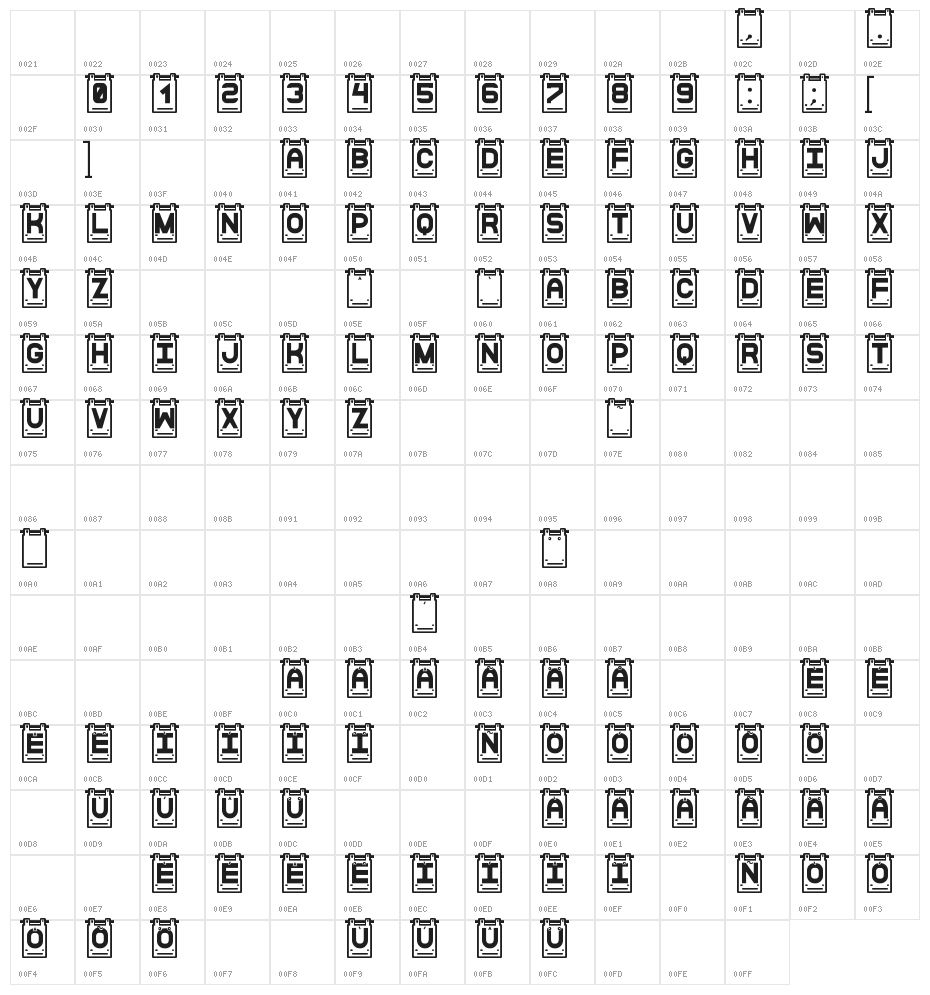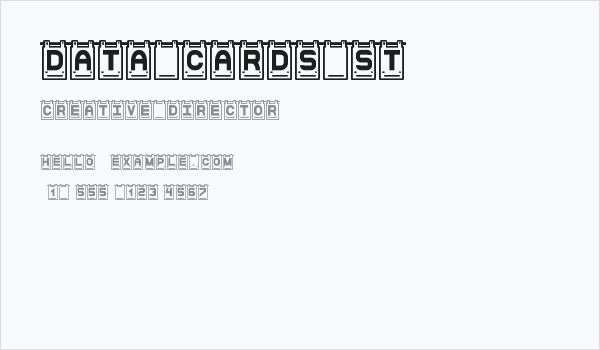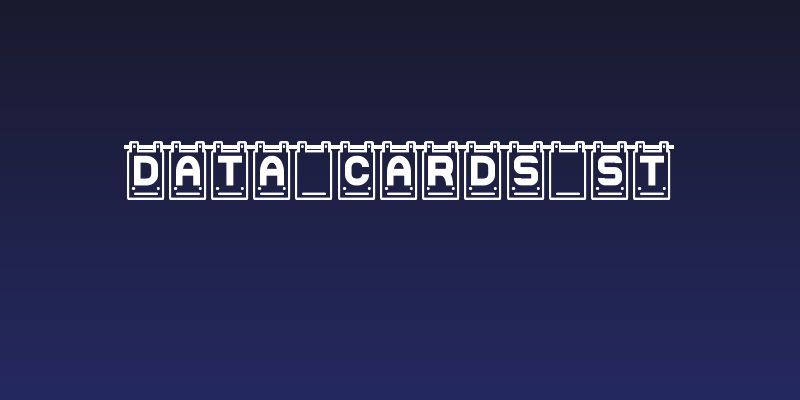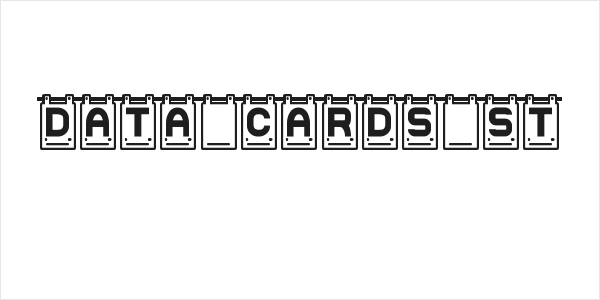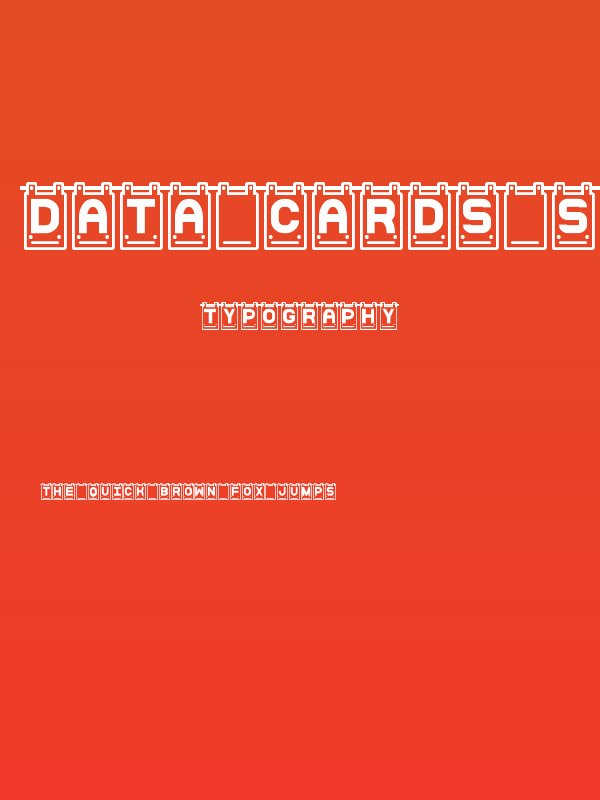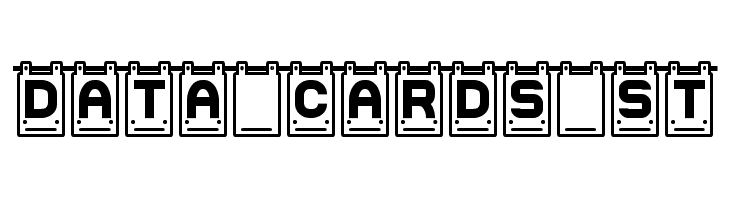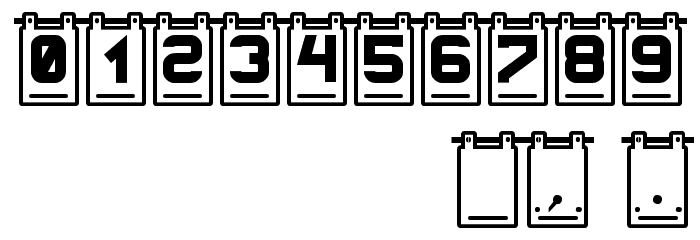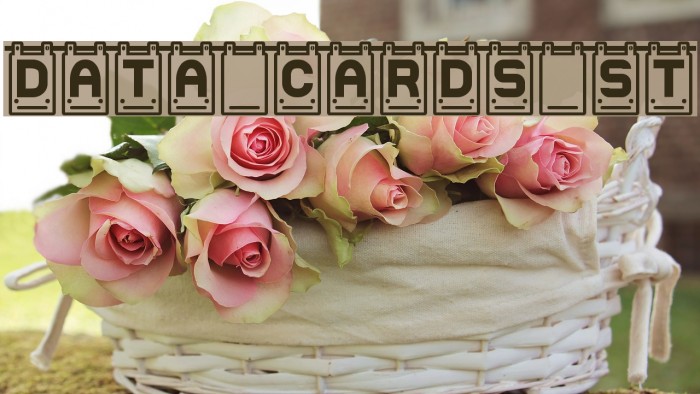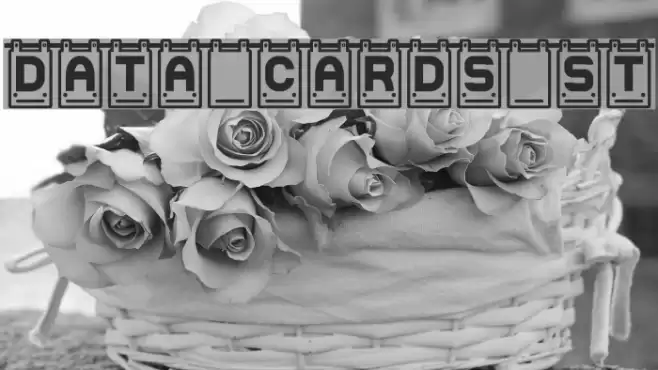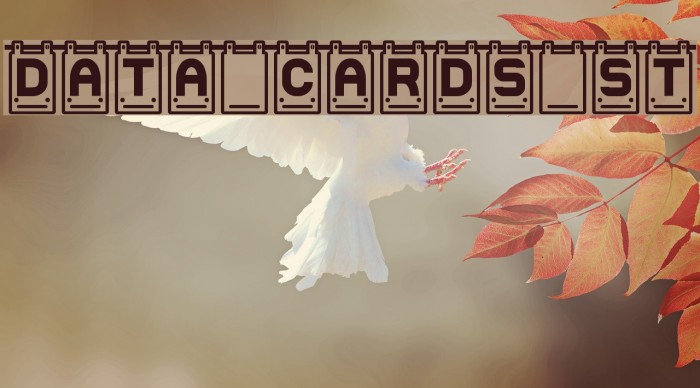
Data Cards St Font
✎ Decorative
| Categorías | Decorative |
| Caso de uso | Headlines, Logos, Signage |
| Proyectos propuestos | Ideal for digital interfaces, retro-themed designs, signage, and branding projects that require a modern yet nostalgic touch. |